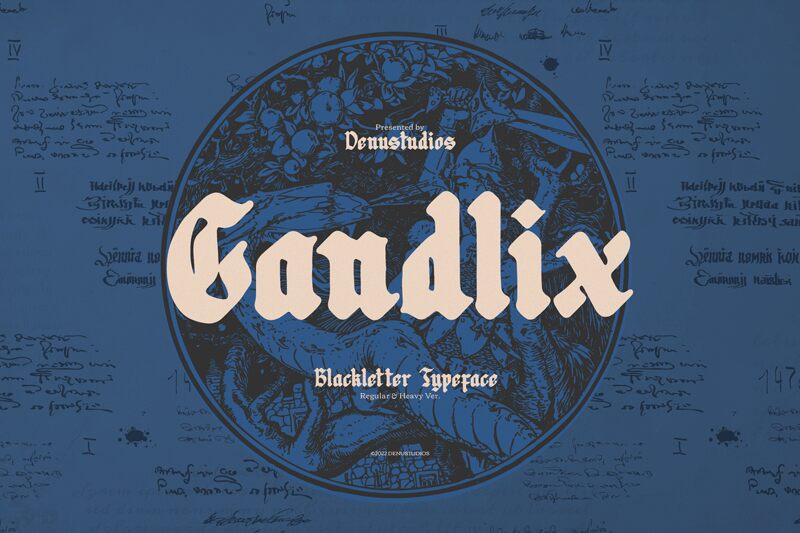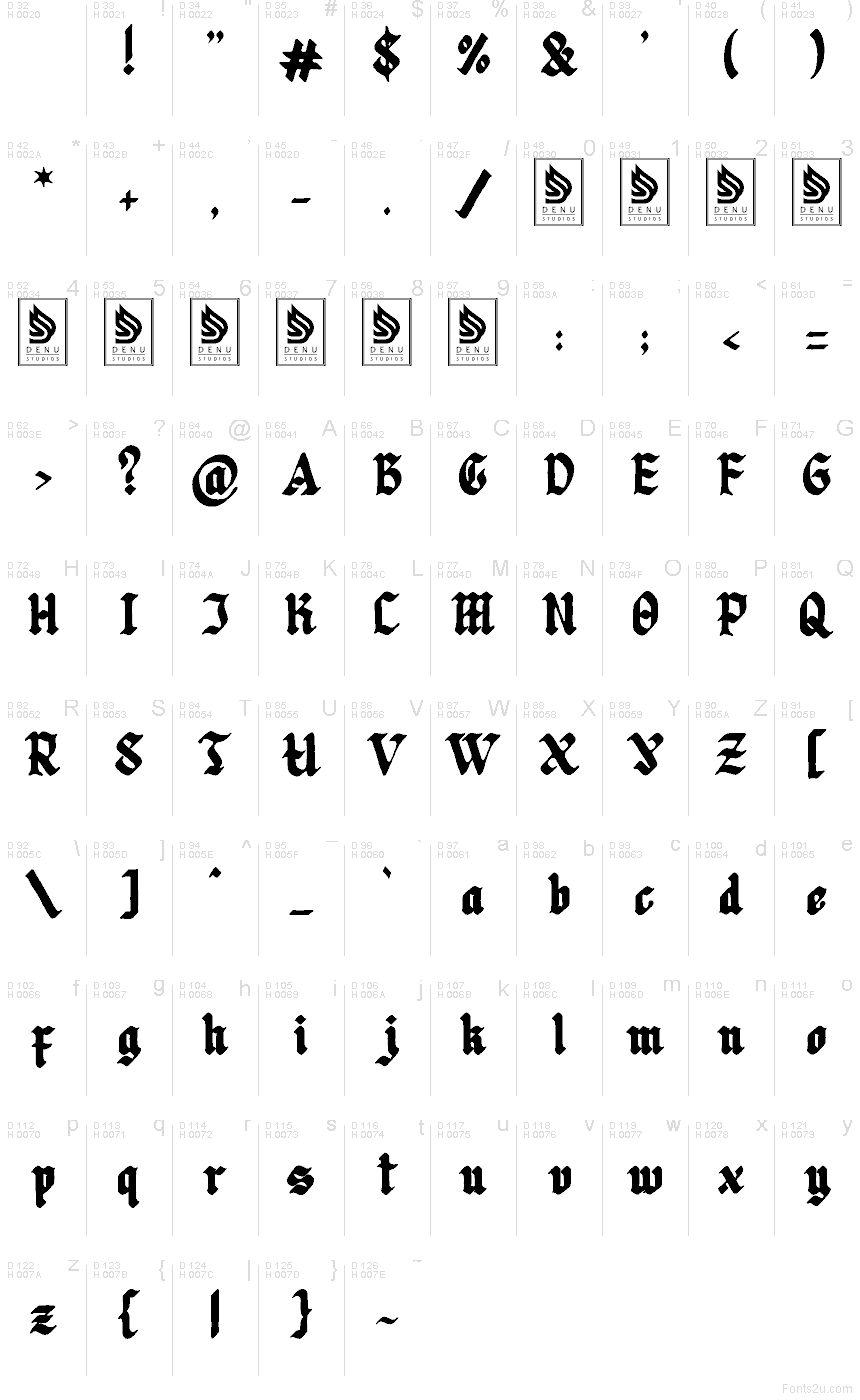
Candlix od Denustudios je moderní gotické písmo zdarma s ostrým charakterem blackletteru. Písmena kombinují robustní středověkou váhu se seříznutými, úhlovými tahy a zářezy ve tvaru diamantů, takže celkový dojem je ceremoniální a trochu přísný, nikoliv starožitně zdobný.
Díky hustým a rytmicky řezaným tvarům se Candlix skvěle hodí pro krátké názvy na obalech, začátky kapitol a titulky, které vyžadují kompaktní gotický akcent. Candlix se hodí pro názvy na plakátech, přebaly alb, branding barů či pivovarů, módní značky, letáky na akce a náladové redakční nadpisy, kde je potřeba kus historie, aniž by písmo působilo jako z vetešnictví.